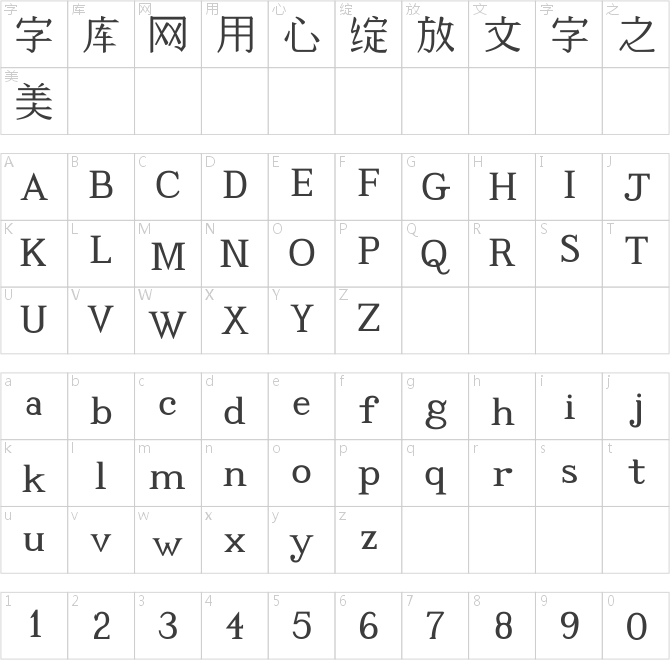
Code2003這是一種經(jīng)典的字體,是一種基于unicode的truetype字體,力求最終以一致的字體表示分配給unicode基本多語言平面的所有擴(kuò)展字符和符號。它的開發(fā)人員試圖創(chuàng)造一個獨特的風(fēng)格或風(fēng)味的字符,同時保持忠實于各種腳本的經(jīng)典字母形式。但是Code2003的字體文件的授權(quán)是SIL授權(quán)的,這一點查看字體文件屬性就可以看到,所以這款字體是遵循SIL Open Font License 1.1授權(quán)協(xié)議 , 可以用于任何用途,包括免費商用。 開放字體許可證(OFL)是由SIL國際維護(hù)的。它試圖在自由軟件和字體設(shè)計社區(qū)的價值觀之間達(dá)成妥協(xié)。它用于幾乎所有開源字體項目,包括Adobe、Google和Mozilla。
CODE2003字體字庫是一款讓人賞心悅目、百看不厭的中文字體,適合各類廣告和產(chǎn)品包裝設(shè)計應(yīng)用,字體大小22.83MB,格式為ttf字體,上傳用戶是dqq520,作者/版權(quán)方為未知